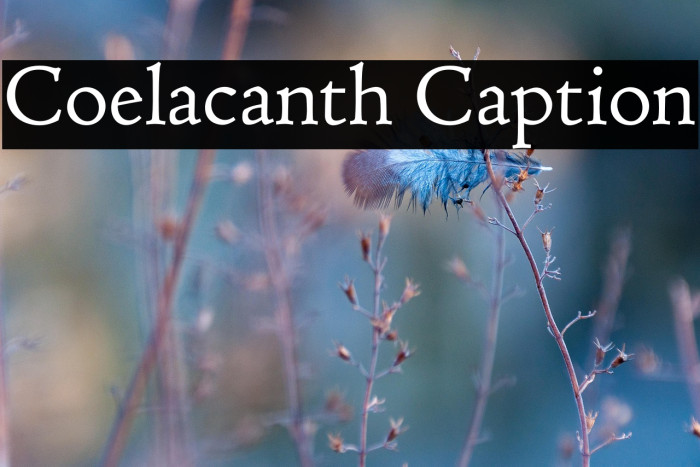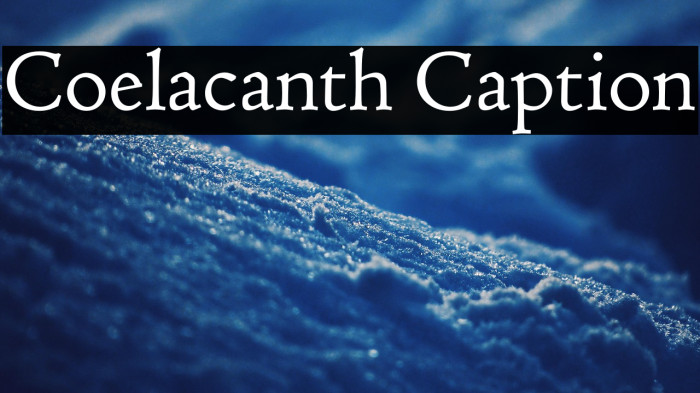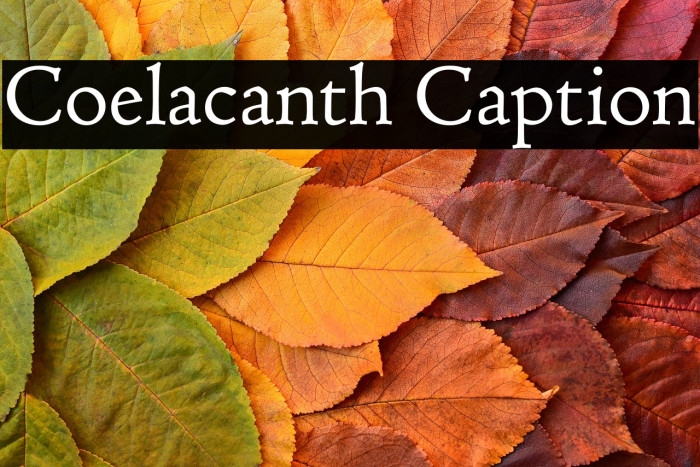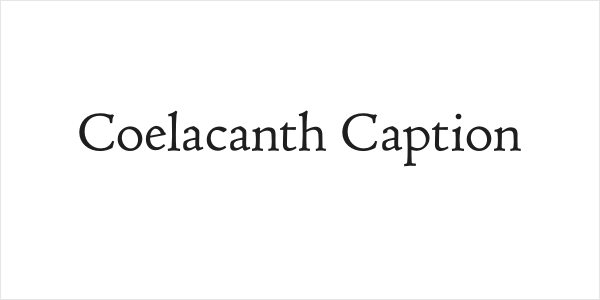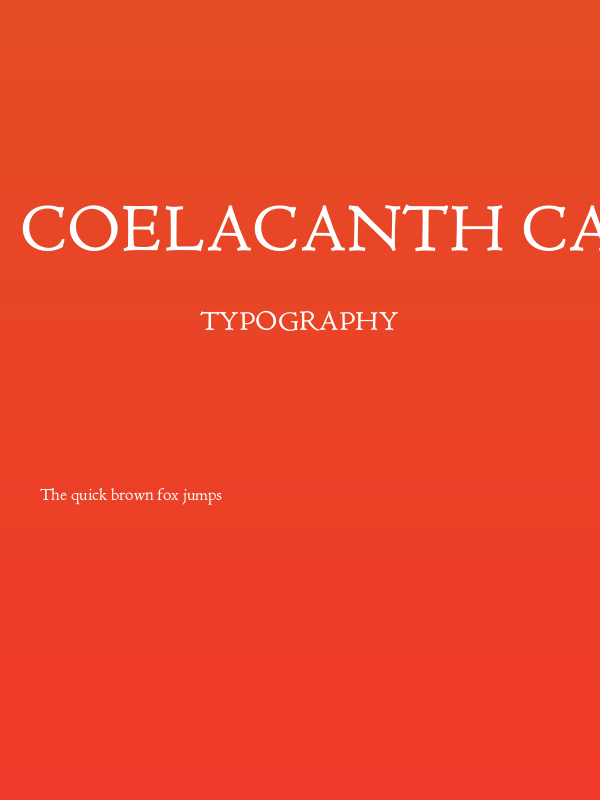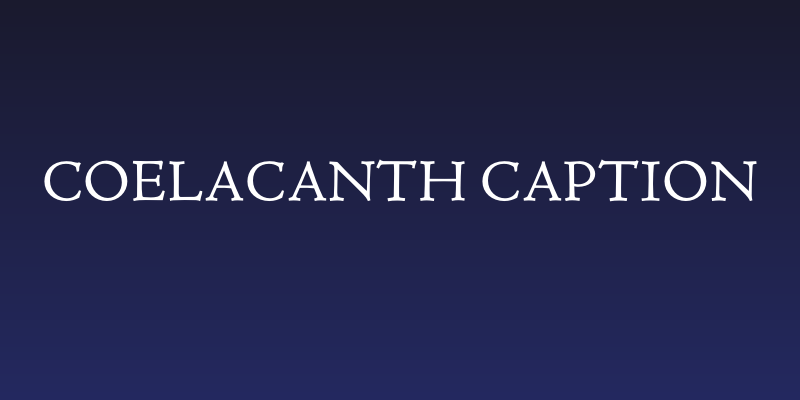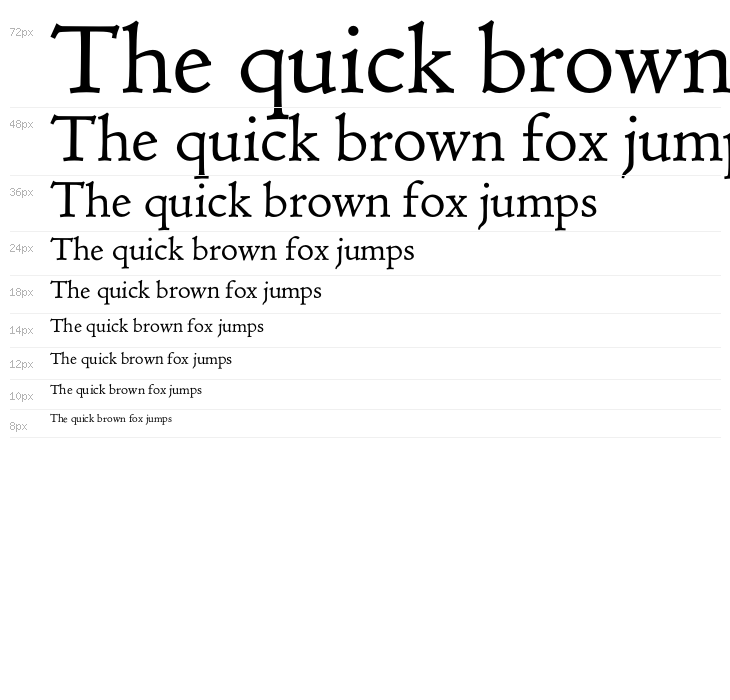
Coelacanth Caption Font
✎ Serif
| 分类 | Serif |
| 整体风格 | Classic |
| 使用场景 | Headlines, Body text, Logos |
| 推荐项目 | Ideal for book covers, historical documents, invitations, and branding that requires a traditional touch. |